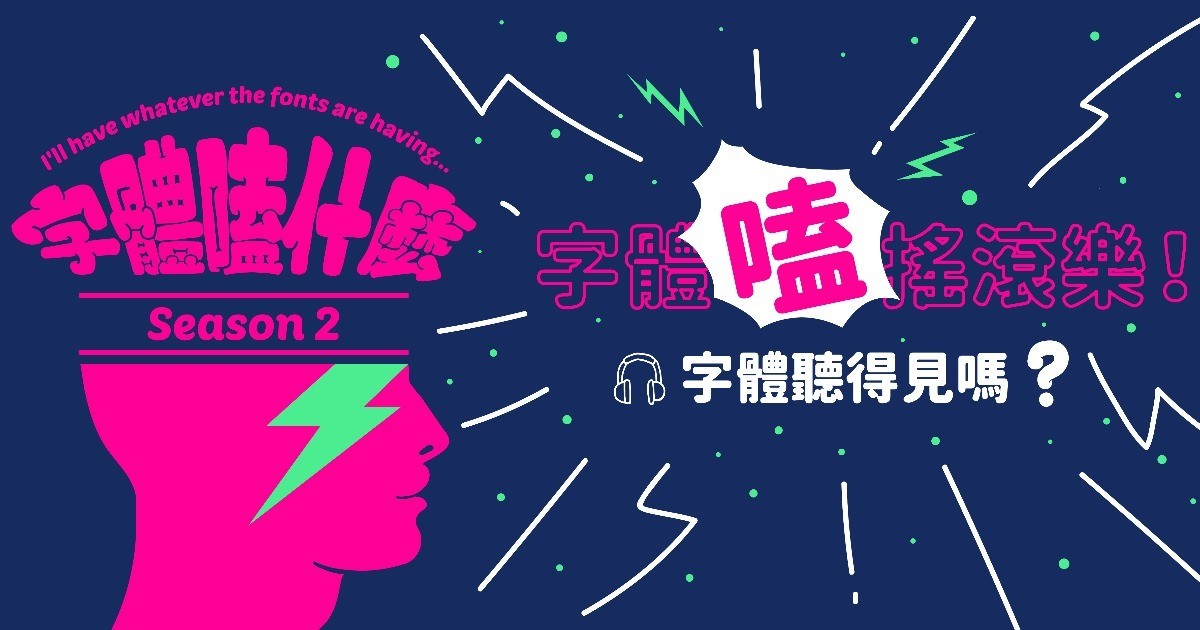
🤯字體嗑什麼🤔
—Season 2—
字體嗑⋯⋯搖滾樂!
關於字體嗑什麼⋯⋯
根據研究,87%的人都不知道字體隨時都有意見,一見面就默默使喚你的大腦。手機、甜食、啤酒;報表、告示、簡報,都要參一腳。不論你靠什麼吃飯,它都要強勢刷存。這也未免太霸道了!
過了半個多世紀仍膾炙人口的搖滾樂,不論你生於何時長於何處,八成都能立刻認出它獨特的頻率。而在你知道一首歌聽起來是激昂或低盪之前,創作者無不費盡心思,想要吸引你按下播放(或下載)鍵。但以什麼工具呢?除了色彩、影像、許多樂迷或樂團都容易忽略的重要環節,就是字體。
人們想不到的是,當目光掃到字體的那瞬間,就對你的潛意識和聽覺產生了影響:這首歌聽起來是刺耳的或平緩的?更甚者是,就連音量和速度,都能夠透過字體來表現嗎?這樣看來,不同時代與風格的搖滾樂,又會如何影響它們的字體運用呢?史上頭一遭,字體不只讓你讀讀看,更要你來「聽聽看」:
- 字體如何影響我們的聽覺
- 搖滾樂的字體長什麼樣子
- 哪一種字體適合哪種曲風
- 來為樂團量身定做字體吧
嘖嘖嘖,像字體這麼控制狂的小東西,千萬別對它一無所知,讓 justfont 說給你聽。不管字體嗑了什麼,都給我來一點!